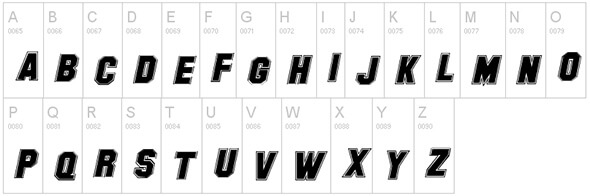
20種類のオールドスクール風フォントを無料でダウンロードする方法
デザイナーにとって、質の高い無料のフォント素材集を使うことは極めて重要なことです。タイポグラフィはどのようなデザインプロジェクトにおいても欠かす事の出来ない重要な要素ですが、フォント素材集は時間短縮に効果的です。
この記事ではあなたの仕事の効率を上げるために役立つ、20種類のオールドスクール風のフォントをフリー素材として入手する方法を紹介していきます。このオールドスクール風のフォントは学校で使う時や、学校がテーマのデザインを行う時などにとても適しています。
クォーターバックファイトフォント
さまざまな自主企画によって、無料でダウンロードでき、使用することが可能な素晴らしいフォントが多数このページに載っています。ぜひ一度、ご自分のスタイルに似合うものがあるかどうか見てみてください。
カレッジドフォント
このフォントはデジタル、紙ものに関係なく、あらゆるものに使用することができます。
カレッジフォント
このフォントはマシューウェルチが作成したものです。個人的な使用は問題ありませんが、商業目的で利用する際には彼に連絡をしてください。
ユニバーシティフォント
この太い線で構成されたフォントはジェロニモの作品です。お試しフォントは紙モノやデジタルもの関係なくあらゆるプロジェクトにご利用いただくことが可能ですが、ライセンスファイルの確認を必ず行ってください。
スティッチンスクールフォント
このユニークなフォントはあらゆるデザインでも美しく映えます。自主企画の場合にはクレジット表記なしで利用することが可能ですが、商業目的の場合にはライセンスの確認をお願いいたします。
ヴィンテージカレッジデットウォーン
このヴィンテージ風のフォントはとても可愛らしく、目を引くこと間違いなしです。ご自身のスタイルに合うかどうか吟味してみてください。
レジェンドM 54
このフォントはシンプルではありますが、きちんと整った感じが目を引く特徴でもあるキャッチーなデザインです。個人的な利用の場合には無料でダウンロードし使用をすることが可能です。
サブロンアップフォント
このフォントはあらゆる企画においても使いやすい、可愛らしくて心強い味方にもなってくれるデザインです。是非見てみて次の企画に利用してみてください。
キャンパス A フォント
こちらは創造において完璧であろうという素晴らしいコンセプトを基にしたユニークなものです。個人的な利用の場合には無料でダウンロードし使用をすることが可能です。
ミッキーズスクールフォント
このフォントはあらゆるプロジェクトに適しています。ポスターやWebサイト、広告なども含めた幅広いものに対応できます。
ユニバーサルカレッジフォント
この可愛らしいフォントはさまざまなプロジェクトで、そのものを目立ちやすくするというユニークな特徴を持ったものです。是非今のご自身のスタイルに合うかどうか検討してみてください。
バンダンハードコアGPフォント
さまざまな状況において役に立つという、興味深いフォントです。この独特なフォントは間違いなく見る者の目を引きます。
IFCハードボールフォント
このすっきりとした印象のフォントはアントンクリロフの作品です。個人的な使用は問題ありませんが、商業目的で利用する際には彼に連絡をしてください。
カレジリオン・バイ・レオナード・ポーザベック
このフォントのデザインは、さまざまなプロジェクトにまとまりを生む効果があります。個人的な使用は費用は発生しませんが、商業目的で利用する際には支払いが生じます。
ガンスクールフォント
このクセのある、太い線のフォントにはすっきりした印象もあります。アイキャッチ効果の高いユニークなデザインです。
ジャージーレターズ
美しい二重線で作られたこのフォントはペリーメイソンの作品です。今のデザインにも、これから先のデザインにもダウンロードして使うことが可能です。
XXII ドント・メス・ウィズ・バイキングス
こちらはレクター・ジョンソンによるデザインです。個人的な使用は問題ありませんが、商業目的で利用する際には彼に連絡をしてください。
ハンドショップタイポグラフィーA 20
こちらは洗練された美しい8種類のフォントを含んだ大きなデザインです。あらゆる企画に無料で使用することができます。
ネブラスカフォント
ネブラスカはダニエルへイッキネンによって作られた目を見張るほど美しいフォントです。美しい太線を持つこのフォントを使えば、あなたの企画が目を引くこと間違いなしです。
バスキュラフォント
ユーザーの目を一瞬で惹きつけるような独特なフォントです。是非ダウンロードをして次の企画に利用してみてください。